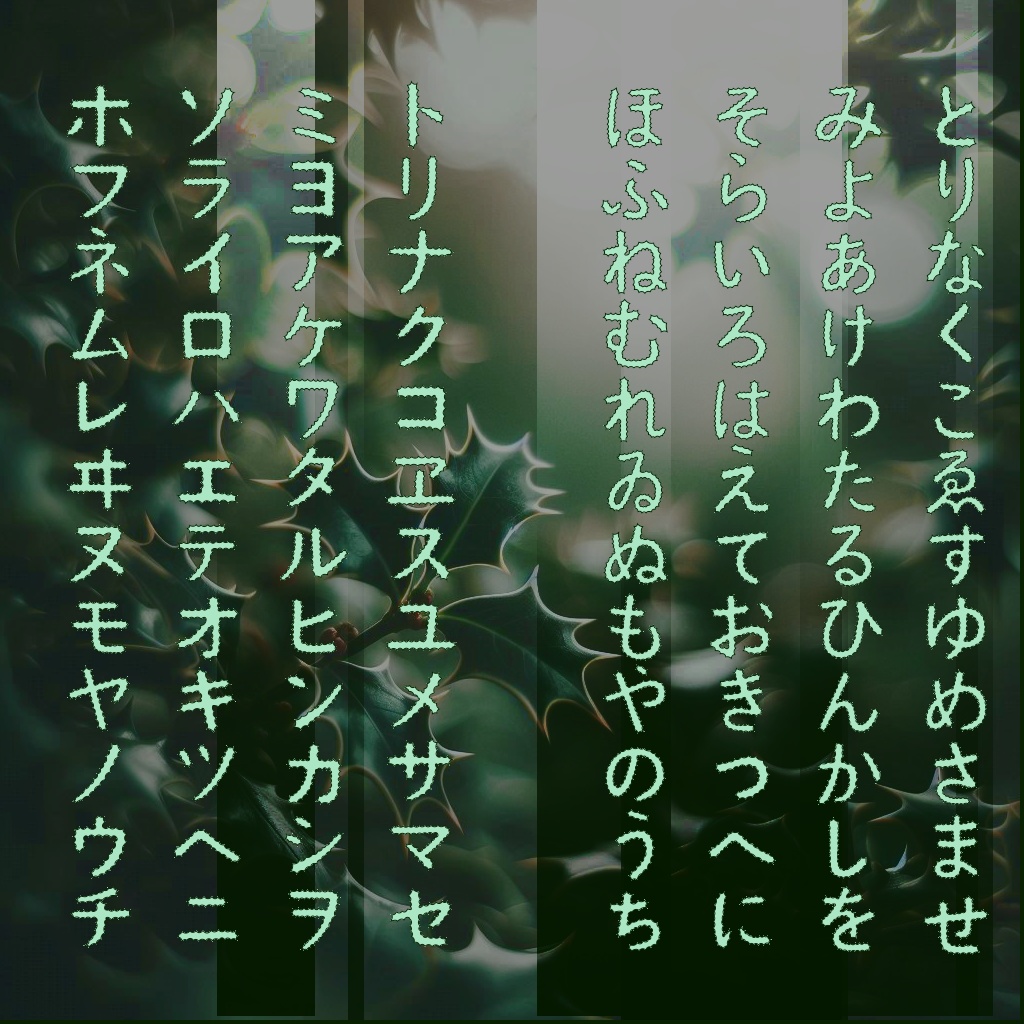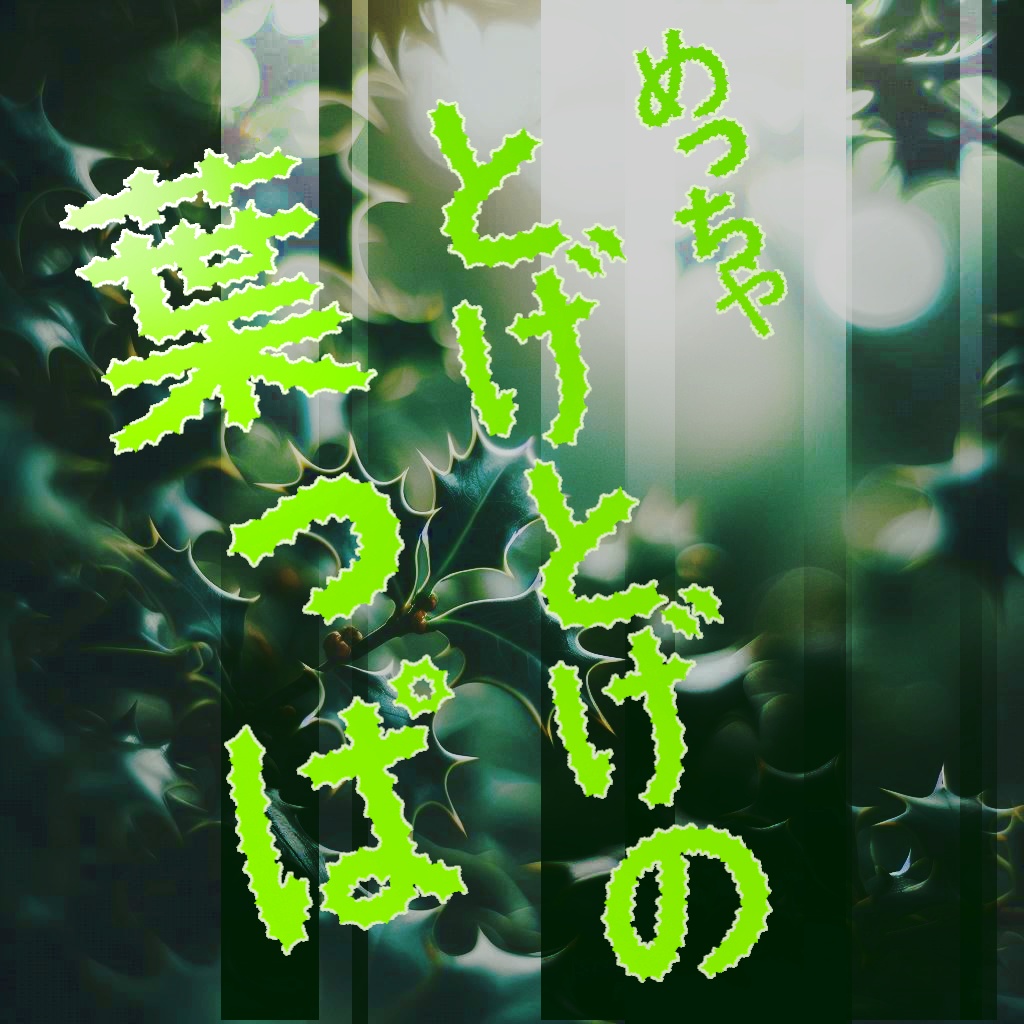
まっつん丸の「柊の葉っぱフォント」【無料・商用利用可】
まっつん丸の舗へようこそ! こちらでは「柊の葉っぱフォント」ご紹介。 柊の葉のような、とげとげフォルム。鋭さの中に、ほんのり丸みを帯びたフォルムが特徴的。そんなデザインフォントです。 シンプルすぎるのは物足りない、でも鋭すぎるのも違う。 そんなあなたにぴったりかもしれません。
英数字・ひらがな・カタカナ・一部記号、漢字の「葉、柊」の 428字 を収録しています。 詳しくは同封のPDFをご参照ください。